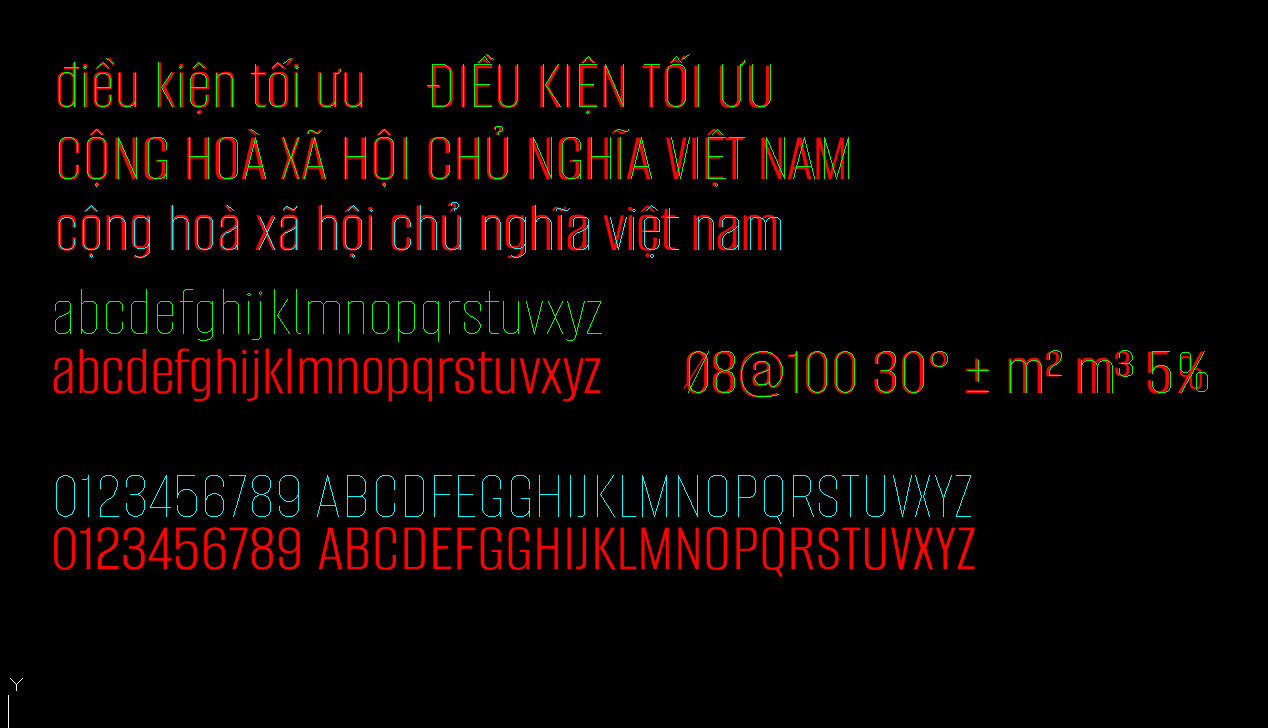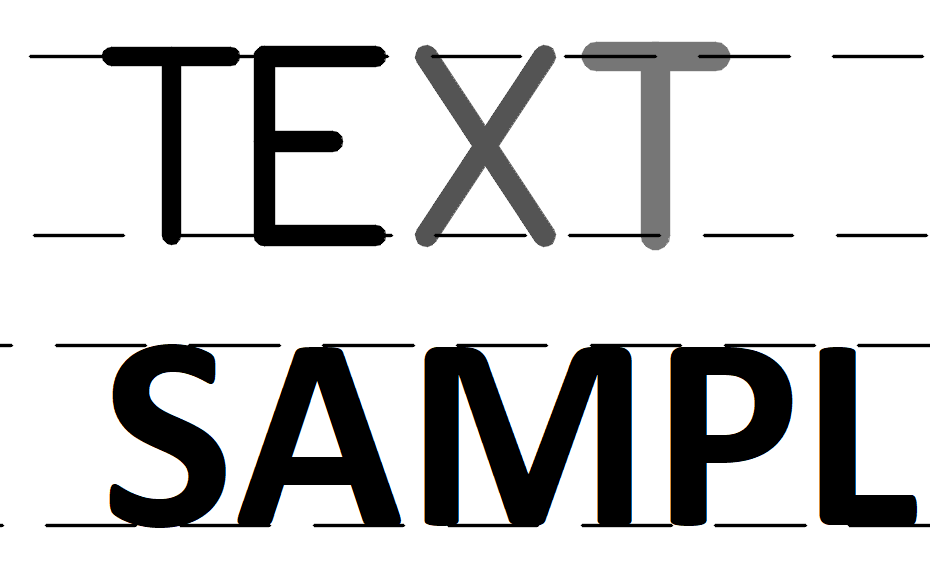
Nhiều kỹ sư và designer khi xử lý bản vẽ thường gặp lỗi thiếu font SHX dẫn đến tình trạng sai lệch ký hiệu hoặc chữ biến thành dấu chấm hỏi. Những trục trặc này làm bản vẽ kỹ thuật trở nên thiếu minh bạch, gây khó khăn cho việc đọc thông số trên bao bì linh kiện. Xưởng In Viva cung cấp hệ thống download font SHX full sắc sảo, giúp bạn hoàn thiện các hồ sơ dự án và ấn phẩm in ấn đạt độ chính xác cao.
Phông chữ font SHX là gì và đặc thù trong ngôn ngữ đồ họa kỹ thuật?
Font SHX là nhóm phông chữ dạng vector được phát triển riêng cho các phần mềm thiết kế kỹ thuật như AutoCAD. Khác với các bộ phông chữ thông thường dựa trên đường viền, dòng VNsimli SHX hay VNsimple SHX được cấu tạo từ các đường thẳng và đường cong đơn giản, giúp máy tính xử lý nhanh chóng các tập tin bản vẽ có dung lượng lớn. Đặc trưng của bộ chữ này là sự tối giản, mảnh mai nhưng cực kỳ chuẩn xác.
Sức hút của dòng phông này nằm ở khả năng hiển thị ổn định trên mọi đời máy in và máy cắt bế. Các mẫu download font 3t Unicode SHXhỗ trợ người dùng gõ tiếng Việt có dấu một cách nhịp nhàng, không lo bị nhảy lỗi bảng mã khi chuyển đổi dữ liệu giữa các đơn vị tư vấn và xưởng sản xuất.
Việc sở hữu bộ font SHX full chất lượng hỗ trợ đơn vị bảo toàn tính thẩm mỹ của các bản hồ sơ năng lực hay bao bì linh kiện.
05 Vai trò thực tiễn của bộ font SHX trong sản xuất vật phẩm thương hiệu
Vẻ đẹp mộc mạc và tính chuẩn xác của mẫu chữ kỹ thuật nâng tầm giá trị cho nhiều ấn phẩm truyền thông của đơn vị:
- Thiết kế bao bì thiết bị công nghiệp: Sử dụng tải font VNsimple SHX để in thông số kỹ thuật trên các dòng vỏ hộp giấy Ivory. Những nét chữ rõ ràng tạo cảm giác minh bạch, giúp khách hàng tin tưởng vào độ chính xác của sản phẩm cơ khí hay linh kiện số.
- Sản xuất bộ ấn phẩm văn phòng cho ngành kiến trúc: Chữ SHX in trên tiêu đề thư hay phong bì tạo phong thái làm việc chuyên nghiệp, nghiêm túc. Đây là phông chữ kinh điển giúp các bản vẽ đối ngoại của đơn vị thi công trở nên đồng bộ và trang trọng hơn.
- Gia công in UV trên các bề mặt máy móc: Logo lồng ghép cùng kiểu chữ kỹ thuật được in trực tiếp trên các sản phẩm mẫu hoặc thiết bị văn phòng. Công nghệ in tại In Viva giúp các đoạn vạch hiển thị sắc sảo, bền màu theo thời gian sử dụng.
- Trang trí voucher và thẻ đặc quyền kỹ thuật: Một dòng chữ mang phong cách bản vẽ trên thẻ thành viên giúp tạo điểm nhấn độc đáo, gợi nhắc về tính nguyên bản và sự tỉ mỉ của thương hiệu.
- Khắc laser tinh xảo trên vật liệu kim loại: Sử dụng tải font CAD full SHX 2020 để khắc mã số hiệu hoặc tên đơn vị lên bút ký. Tệp vector chuẩn giúp máy khắc đi nét mượt mà, tạo độ sâu sắc nét cho từng ký tự mảnh mà không bị nhòe.
04 Lưu ý kỹ thuật khi xử lý font SHX phục vụ gia công thực tế
Để hệ thống ký tự vector hiển thị sống động và bền màu trên các thành phẩm thực tế như túi giấy cao cấp hay nhãn mác công nghiệp, designer cần chú trọng:
- Kiểm soát độ mảnh của nét vẽ: Các mẫu VNsimli SHX thường có nét rất thanh. Designer nên điều chỉnh độ dày đường viền (Stroke) phù hợp để khi in lụa hoặc khắc laser, mực bám ổn định, tránh tình trạng chữ bị đứt đoạn hay mờ nhòe dưới tác động của nhiệt độ.
- Tối ưu đường Path cho gia công bế nổi: Bước này đặc biệt quan trọng khi sản xuất nắp hộp cứng dập nổi logo doanh nghiệp theo phong cách bản vẽ CAD. Kỹ thuật viên cần làm mượt từng điểm neo vuông vức trong file vector giúp khuôn bế thực hiện chính xác, tạo hiệu ứng nổi khối rõ nét mà không làm rách giấy Ivory.
- Thiết lập hệ màu CMYK cho bản vẽ in ấn: Designer cần hiệu chỉnh hệ màu CMYK chuẩn tại xưởng và yêu cầu in mẫu thử để đảm bảo màu chữ sau in không bị ám xám hay mất sắc độ so với bản vẽ tải font CAD full SHX 2021 trên máy tính.
- Chuyển đổi sang Polyline trước khi gia công: Đối với các nhu cầu cắt bế hoặc khắc, bạn nên đảm bảo các ký tự đã được chuyển đổi sang đường khép kín. Việc này giúp máy gia công tự động vận hành trơn tru, không gây lỗi đứt nét hay nhăm nhở bề mặt vật liệu giấy và nhựa.